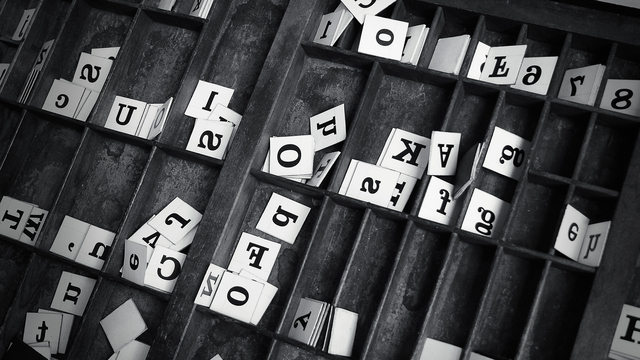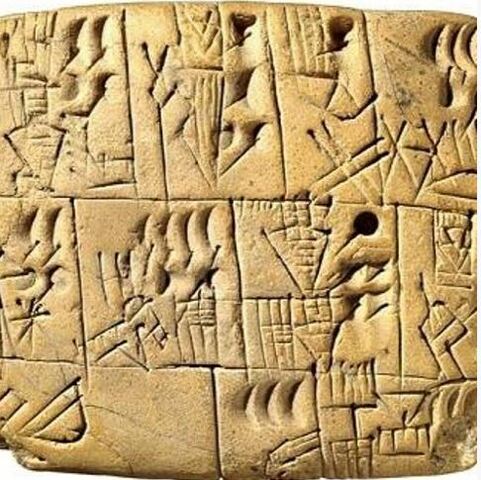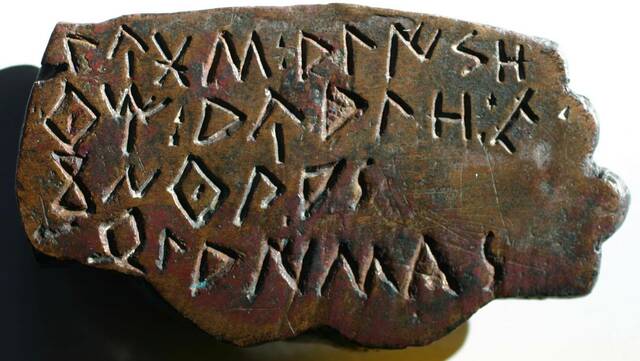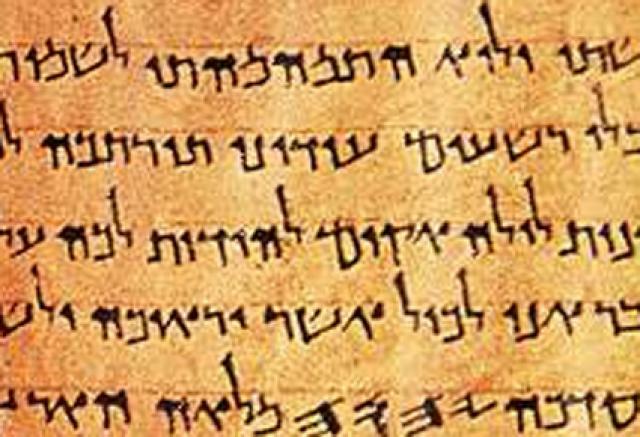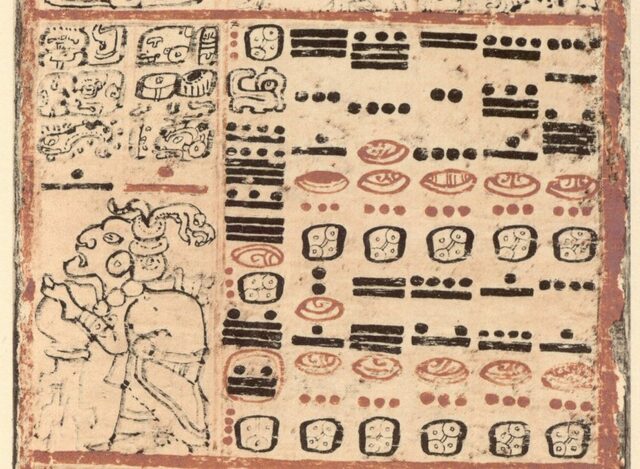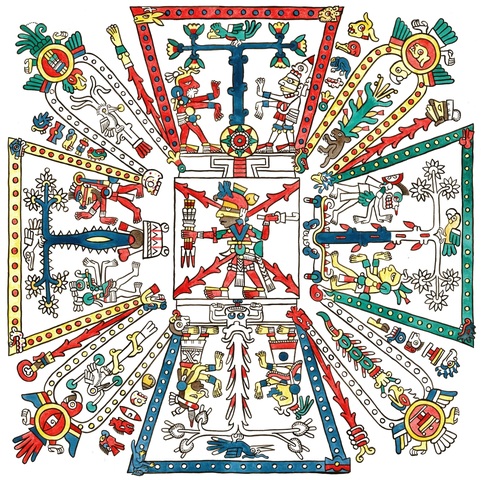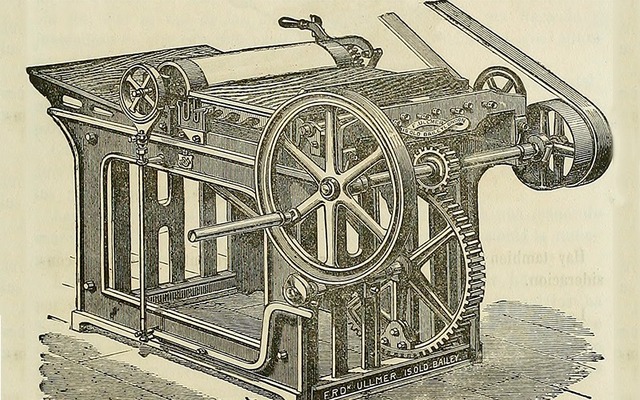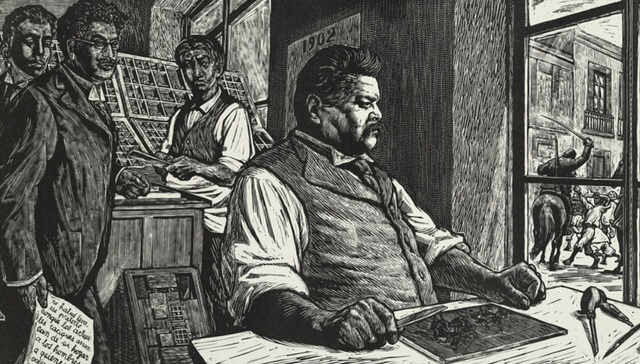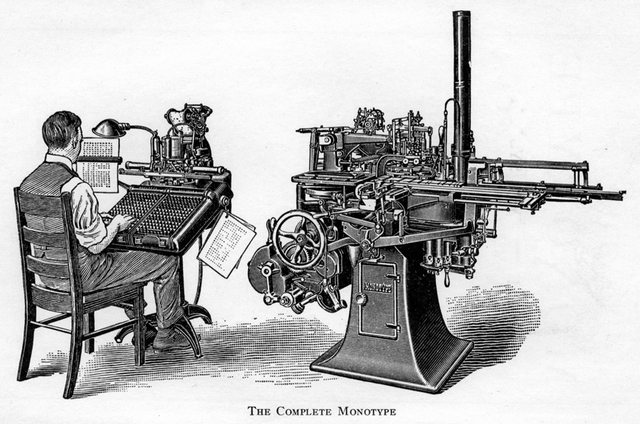
(ÁSIA)
Civilización sumeria. Asentada en Siria e Irak, es la primera en generar un sistema de escritura denominado uniforme y caracterizado por basarse en una estructura triangular. -
(EUROPA)
Mesopotamia. Surge el primer sistema de escritura denominado cuneiforme. A Cargo de los sumerios. -
(ÁFRICA)
La primera escritura pictográfica fue atribuida a los egipcios, escritura en rollos de papiro. -
(ASIA)
En China se desarrolla el sistema ideográfico, representando ideas o conceptos mediante símbolos. -
(EUROPA)
Los fenicios desarrollan un sistema fonético que sirvió de base para el alfabeto actual, coludido a 22 símbolos mágicos. -
(EUROPA)
Los griegos toman como antecedente al alfabeto fenicio agregando términos al mismo. Dando los principios de las vocales. Fue diseñado para leerse en bustrófedon o diferentes direcciones. -
(ASIA)
La cultura hebrea desarrolla su propio sistema de escritura cuadrado. Usado hasta la fecha. -
(ASIA)
Invento del papel en China. Cai Lun utiliza fibras naturales para su creación. -
(AMÉRICA)
En el actual territorio de la república mexicana, en lo que alguna vez fue Teotihuacán; se desarrollan los murales pictográficos. -
(EUROPA)
La civilización romana mejora la forma de las letras en base a fundamentos geométricos. Dando paso al legado de la estructura actual. -
(EUROPA)
Edad media. Se da paso a la creación de letras copistas, más fáciles de transcribir en los monasterios. -
(ASIA)
Creación del sistema de Knjis en Japón de manera forzada. -
(AMÉRICA)
En el actual área de la república mexicana. El imperio maya se encarga de crear un sistema de escritura fonético, escritura por medio de glifos, aunado a numeración aplicada en matemáticas y astronomía. -
(ASIA)
Los Islámicos desarrollan un sistema de escritura llamado “Jazm”. -
(EUROPA)
A la mitad de la edad media Carlo Magno decide mandar a estructurar un tipo de letra específico bajo el fin de estandarizar estilos caligráficos. Desarrollando la primera versión de las letras minúsculas. -
(EUROPA)
El monje Cirilo, inventa el alfabeto cirílico. -
(ASIA)
Bi Sheng desarrolla por primera vez tipos móviles. Cubos metálicos con letras y/o símbolos grabados para imprimir de manera rápida. -
(EUROPA)
Primeras fábricas de papel se establecen en España. Con ayuda del papel como un material rugoso, duro y difícil de obtener. -
(EUROPA)
Francia y Alemania, le dan textura visual al texto con ayuda del estilo gótico. -
(EUROPA)
En España e Italia se desarrolla el rotunder o diseño más redondo. -
(AMERICA)
La civilización mexica elabora códices con elementos pictográficos como medio de expresión. -
(AMÉRICA)
Desarrollo del sistema a base de nudos, llamado “quipus” por los incas, en Perú. El Quipu era una herramienta que utilizaban los Incas para llevar el registro y la contabilidad. -
(EUROPA)
Alrededor de 1456 Guntenberg termina de imprimir la famosa biblia de 42 líneas mejorando el sistema de móviles chino. Imprimiendo en letra gótica el primer libro, excluyendo al idioma latín de él. -
(EUROPA)
Aldo Manucio funda la IMPRENTA ALDINA. El diseño de la letra itálica estuvo a cargo de Francesco Griffo. Son los creadores de la letra cursiva. -
(AMÉRICA)
Después de la conquista llega la primera imprenta a América. Juan Pablos o también llamado Giovanni Paoli fue el encargado de establecerla y distribuirla entre la lengua náhuatl. -
(EUROPA)
Claude Garamond, establece la imprenta real, cambia el estilo de la letra, llamándola “griega”. -
(ASIA)
La cultura árabe presenta y desarrolla un estilo caligráfico peculiar basado en una apariencia zoomórfica. -
(EUROPA)
La revolución industrial impulsa al sector tipográfico hacia fines comerciales. William Caslon genera un linaje tipográfico de 4 generaciones. -
(EUROPA)
John Baskerville mejora la tinta y el papel tipografía de transición. Su alfabeto es símbolo de elegancia. -
(EUROPA)
Giambattista Bodoni, diseña el primer tipo de letra moderna. -
(EUROPA)
Sbnefelder inventa la litografía, sistema de impresión que permite la reproducción de colores. -
(EUROPA)
William Calson IV, crea el primer tipo de letra sin patines. -
(EUROPA)
William Morris imprime libros artesanales Arts and Crafts. -
(AMÉRICA)
En México, nace el taller de la gráfica popular a cargo de José Guadalupe Posadas. -
(EUROPA)
Ottmar Megenthaler inventa la maquina de linotipo. -
(EUROPA)
En Francia, nace el estilo Art Nouveau. -
(EUROPA)
Walter Gropius, funda la primera escuela dedicada a la enseñanza del diseño, llamada “Bauhaus”. -
(EUROPA)
Stanley Morison crea la afamada fuente Times New Roman. -
(EUROPA)
Herbert Bayer y Jan Tschichold, diseñan tipos de letras funcionalistas. -
Surgen dos grandes tipos de letras:
• Gill Sans (Eric Gill) Inglaterra
• Futura (Paul Renner) Alemania -
(AMÉRICA)
Surge en México la tipografía vernácula creada por los rotulistas. -
(AMÉRICA)
Una vez culminada la segunda guerra mundial, en 1947 se termina de construir la primera computadora electrónica llamada ENIAC, en la universidad de Pensilvania, dando inicio a la eras digital de la tipografía y el diseño. -
(EUROPA)
El tipógrafo alemán Hermann Zapf diseña las fuentes Optima y Palatino. -
(EUROPA)
Max Miedinger concreta el diseño de la fuente Helvética. -
(EUROPA)
Adrian Frutiger diseña su tipo de letra Universe.
Su tipo de letra frutiger, es usada como señalización en todos los aeropuertos del mundo. -
(AMÉRICA)
Aparece la fotocomposición en los Estados Unidos, estrategia de impresión que permitía la reproducción fidedigna del material a imprimir. -
(AMÉRICA)
En los Estados Unidos estallan los movimientos psicodélicos. Caracterizados en el área tipográfica por inducir letras de carácter más visual y complejo. -
(AMERICA)
Susana Licko y Rudy VanderLans, realizaron tipografía experimental en la revista Emigre, diseño a computadora. -
(AMERICA)
Comercialización de la primera computadora personal, Macintosh. -
(AMÉRICA)
Deconstructivismo por David Carson -
(AMÉRICA)
Diseñadores mexicanos comienzan a crear tipografías. -